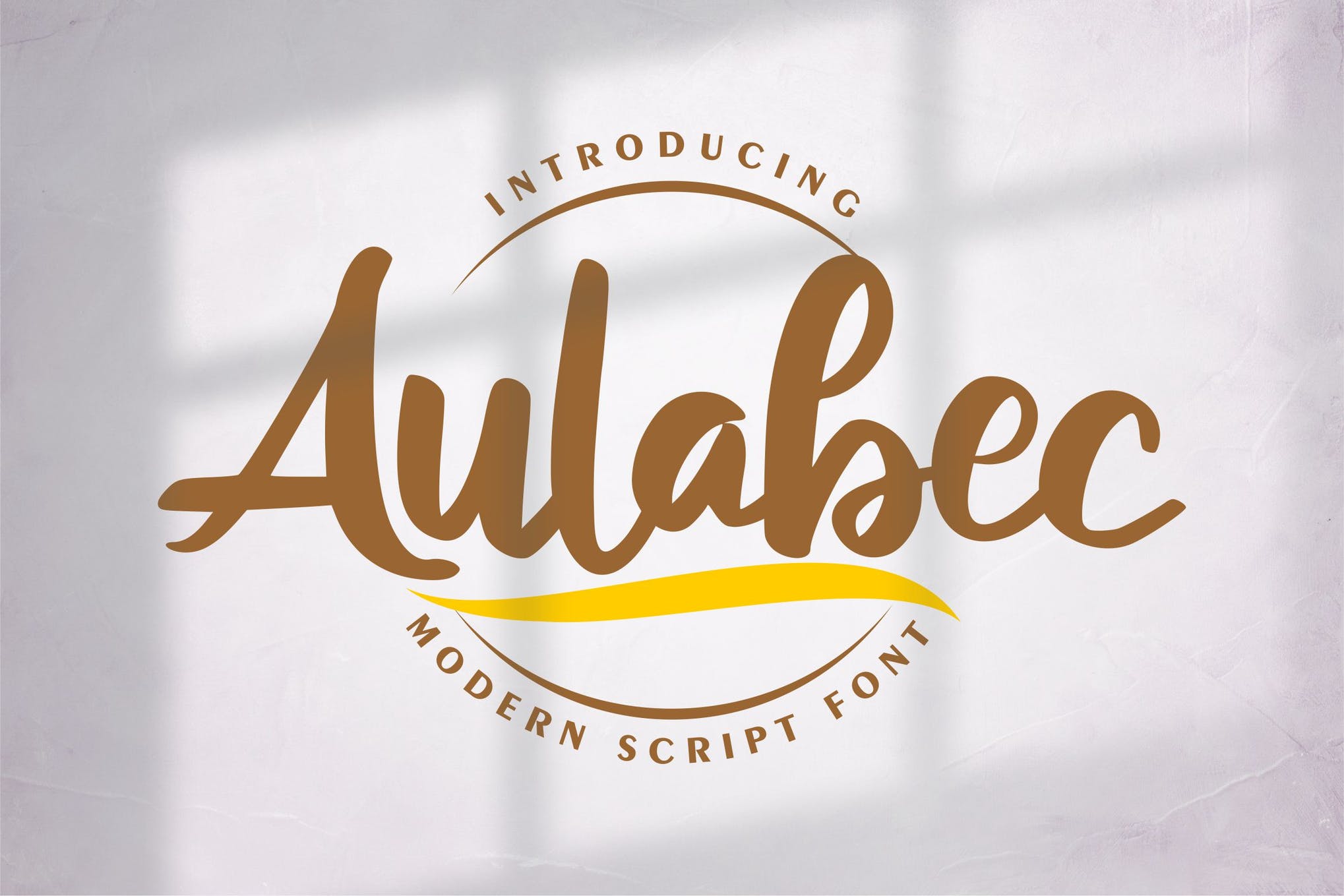
Aulabec | Modern Script Font with a calligraphy style, So beautiful on invitation like greeting cards, branding materials, business cards, quotes, posters, and more!